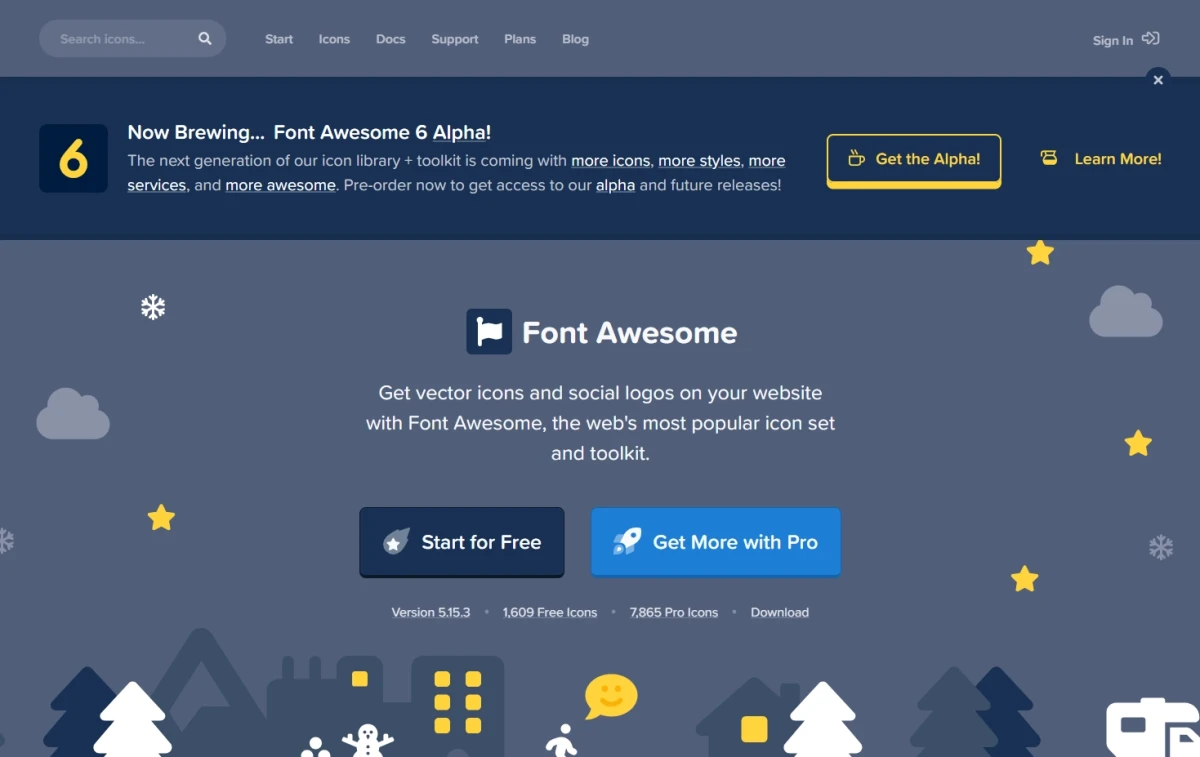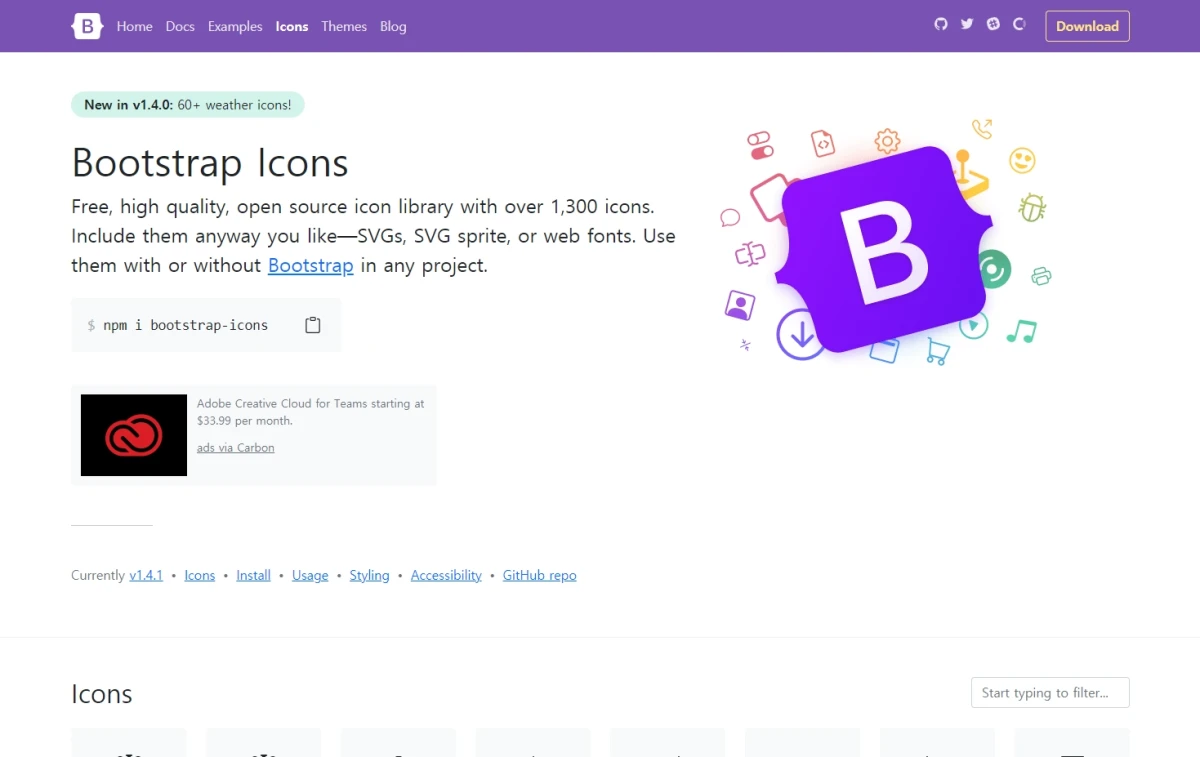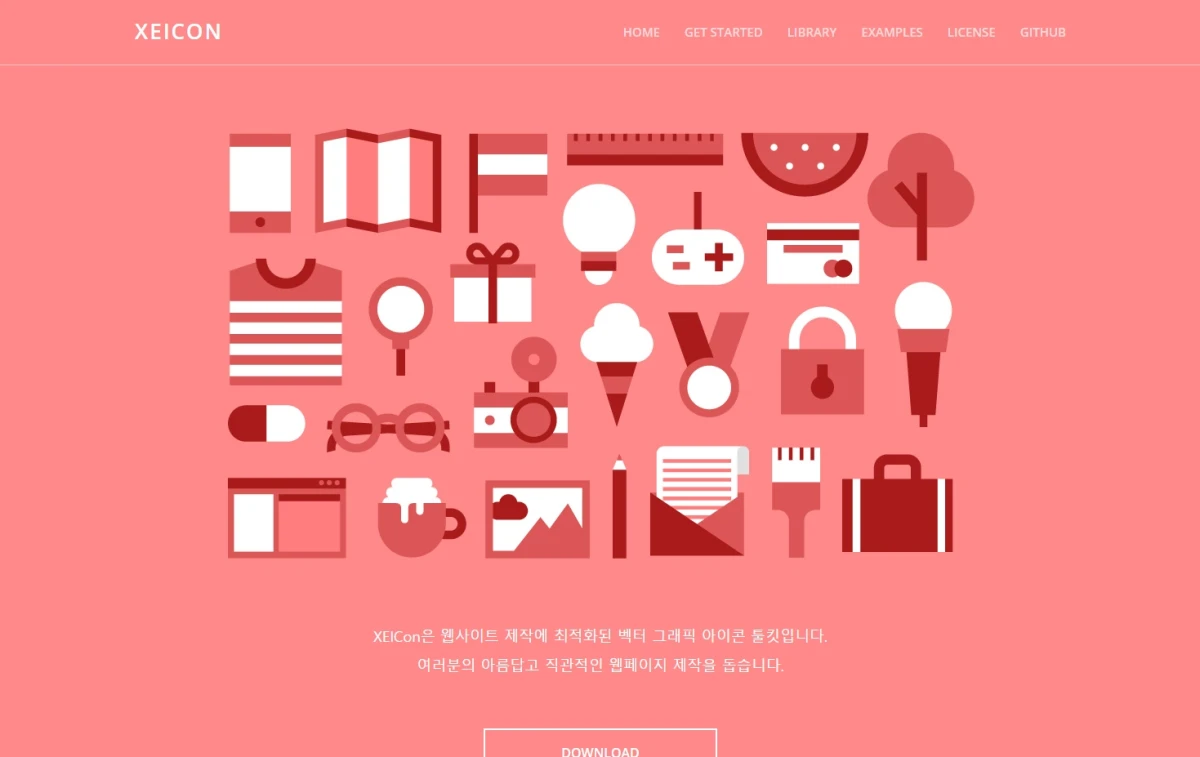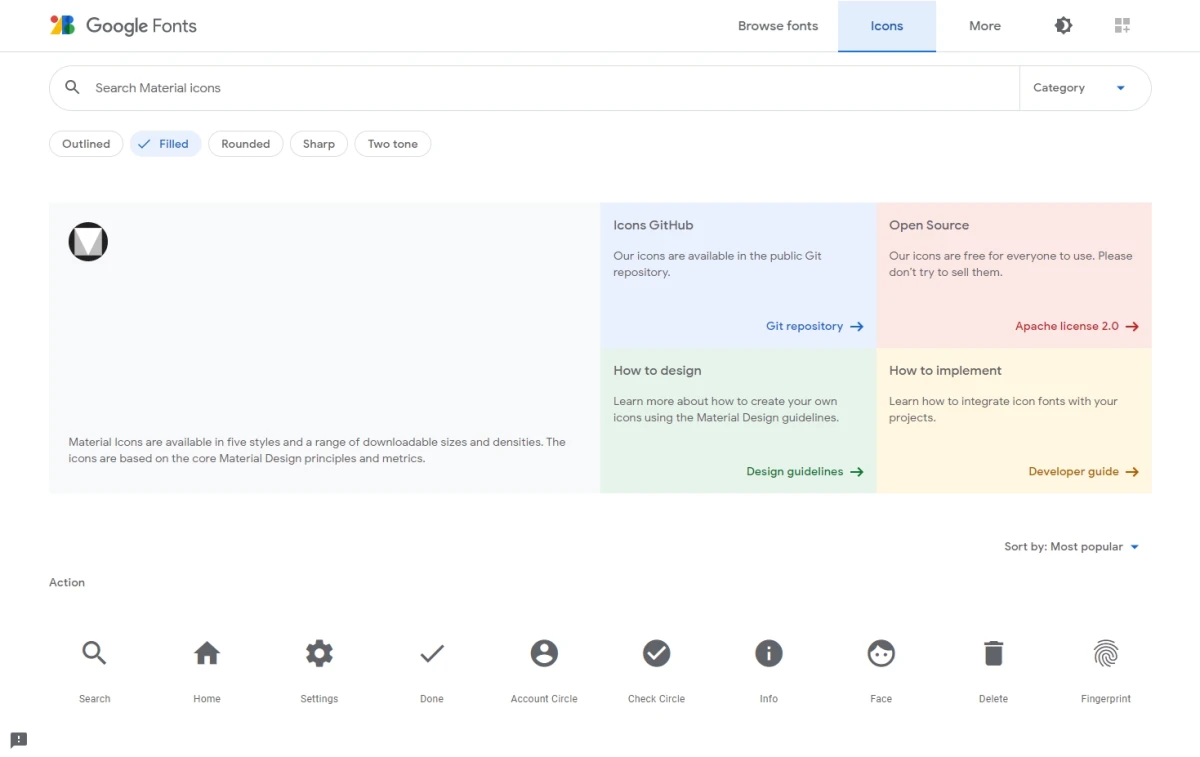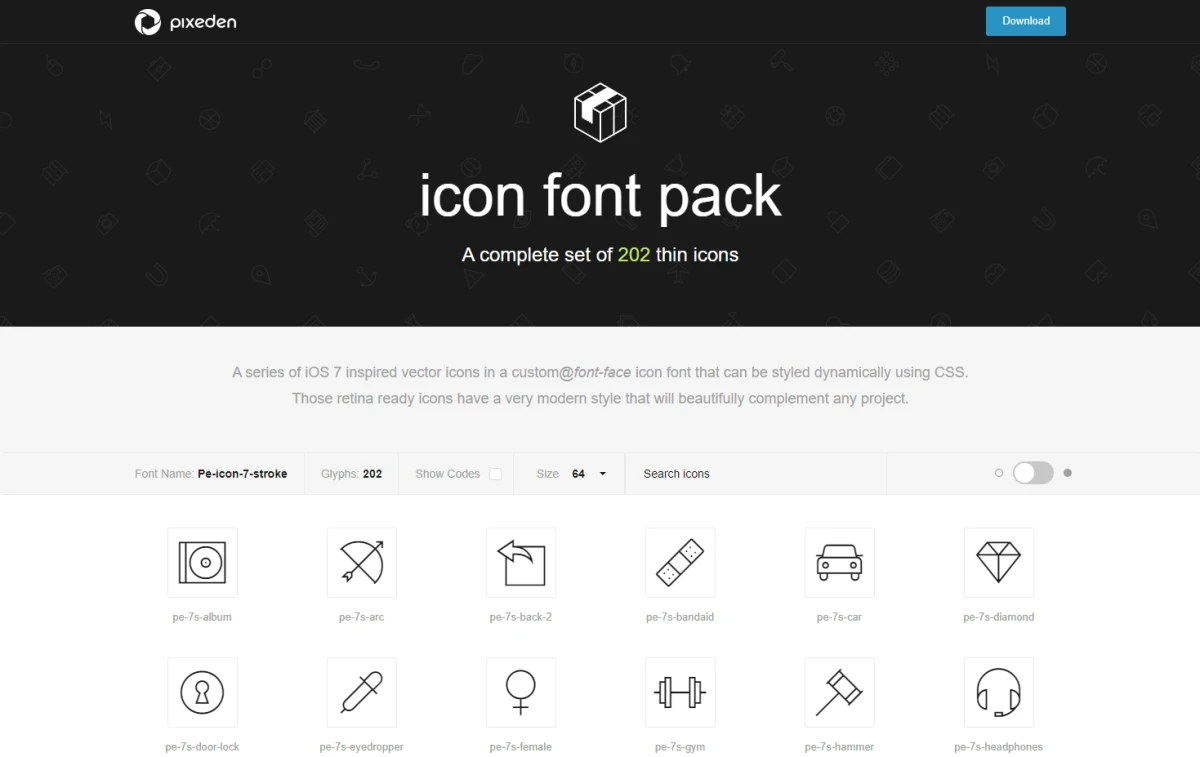
웹사이트 아이콘 폰트와 SVG 아이콘, 무엇을 써야 할까?
아이콘 폰트는 클래스 추가만으로 적용하기 쉽지만 전체 폰트 파일을 불러와 용량이 큽니다. SVG 아이콘은 필요한 것만 불러와 가볍고 선명하지만 마크업 관리가 늘어납니다. 사이트 제작 방식에 맞춰 선택하는 것이 좋습니다.
SNS 로고를 넣거나 전화, 이메일 같은 연락처 아이콘을 표시할 때, 또는 사진 대신 가벼운 라인 아이콘으로 UI를 정리하고 싶을 때 아이콘을 찾게 됩니다. 그런데 막상 찾아보면 폰트어썸처럼 오래 쓰인 아이콘 폰트도 있고, 루시드(Lucide)나 타블러(Tabler)처럼 최근 React, Vue 프로젝트에서 더 많이 보이는 SVG 라이브러리도 있습니다. 둘은 적용 방식부터 다르기 때문에, 사이트 성격에 따라 선택이 갈립니다.
아이콘 폰트와 SVG 아이콘의 차이
아이콘 폰트는 글자처럼 동작하는 폰트 파일입니다. CSS 클래스 하나만 추가하면 아이콘이 표시되고, 색상이나 크기도 텍스트처럼 조정할 수 있어 적용이 단순합니다. 반면 SVG 아이콘은 이미지 형태의 벡터 파일로, 필요한 아이콘만 골라 코드에 직접 넣는 방식입니다.
이 차이가 실제로 영향을 주는 부분은 로딩 속도와 화면 표시 품질입니다. 아이콘 폰트는 몇백 개 아이콘이 들어 있는 폰트 파일 전체를 불러오기 때문에, 실제 쓰는 아이콘이 몇 개뿐이어도 파일 용량은 그대로입니다. 폰트 파일이 늦게 로드되면 텍스트처럼 취급되는 아이콘이 잠깐 깨진 사각형으로 보이는 현상도 생길 수 있습니다. SVG는 사용하는 아이콘만 불러오므로 용량이 가볍고, 해상도와 무관하게 선이 또렷합니다. 다만 아이콘 수가 많아지면 마크업에 SVG 코드가 하나씩 들어가야 해서 관리할 파일이 늘어난다는 단점이 있습니다.
오랜 기간 쓰여온 아이콘 폰트
워드프레스 테마나 부트스트랩 기반 사이트, 또는 코드를 직접 다루지 않고 HTML 클래스만 추가해 아이콘을 넣고 싶은 경우라면 아이콘 폰트 쪽이 여전히 적용하기 쉽습니다.
아이콘 폰트 중에는 특정 디자인 콘셉트에 맞춘 세트도 있습니다. 예를 들어 픽세덴 스트로크 아이콘은 플랫 라인 스타일을 일관되게 적용하고 싶을 때 골라 쓰기 좋습니다.
아이콘 폰트 파일 안에 어떤 아이콘이 들어 있는지 미리 확인하려면 폰트드롭 서비스를 이용하면 편리합니다.
최근 많이 쓰이는 SVG 아이콘
React, Vue 같은 프레임워크로 제작하는 사이트가 늘면서 SVG 아이콘을 컴포넌트 형태로 바로 불러오는 방식이 자리잡았습니다. 필요한 아이콘만 선택해 가져오는 트리쉐이킹(tree shaking)이 가능해 번들 용량 관리에 유리하다는 점이 이 흐름이 자리잡은 이유입니다.
상황별로 정리하면
상황 적합한 방식
코드를 직접 다루지 않고 클래스 추가만으로 적용 폰트어썸, XE아이콘, 부트스트랩 아이콘
React, Vue 기반 사이트로 번들 용량을 관리해야 함 루시드, 헤로아이콘, 타블러
네이버, 카카오 같은 국내 서비스 아이콘이 필요함 XE아이콘
아이콘 수가 많이 필요한 대시보드, 관리자 화면 타블러, 폰트어썸
구글 디자인 가이드를 따르는 사이트 머티리얼 심볼
한 사이트 안에서 아이콘 스타일이 섞이면 디자인이 산만해 보이기 쉽습니다. 제작 방식이 정해졌다면 그 안에서 한 가지 아이콘 체계를 고르고, 이후 추가되는 아이콘도 같은 체계 안에서 찾는 편이 정리된 인상을 줍니다.